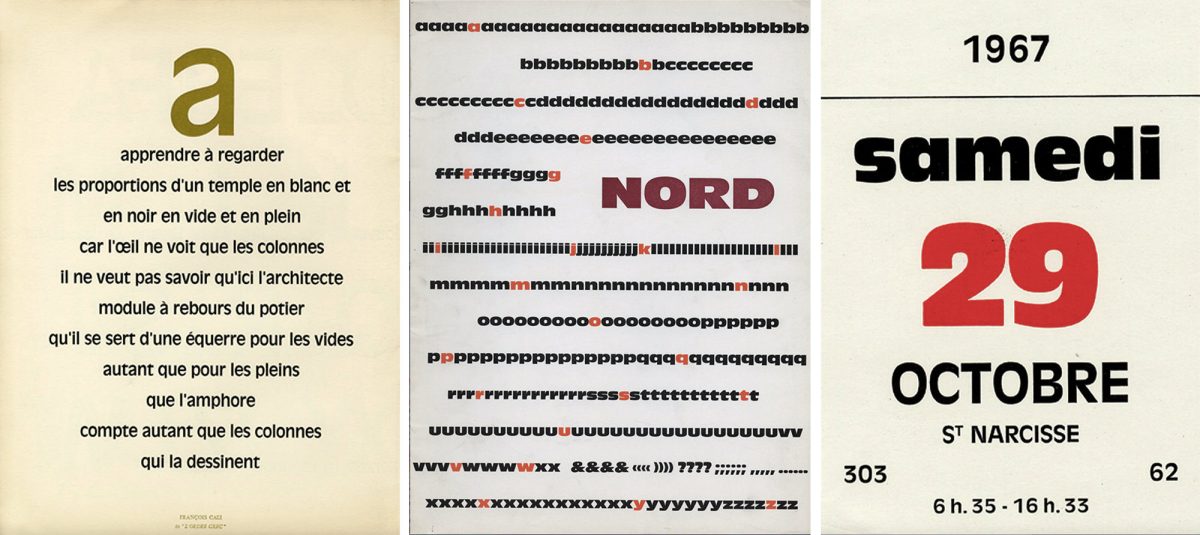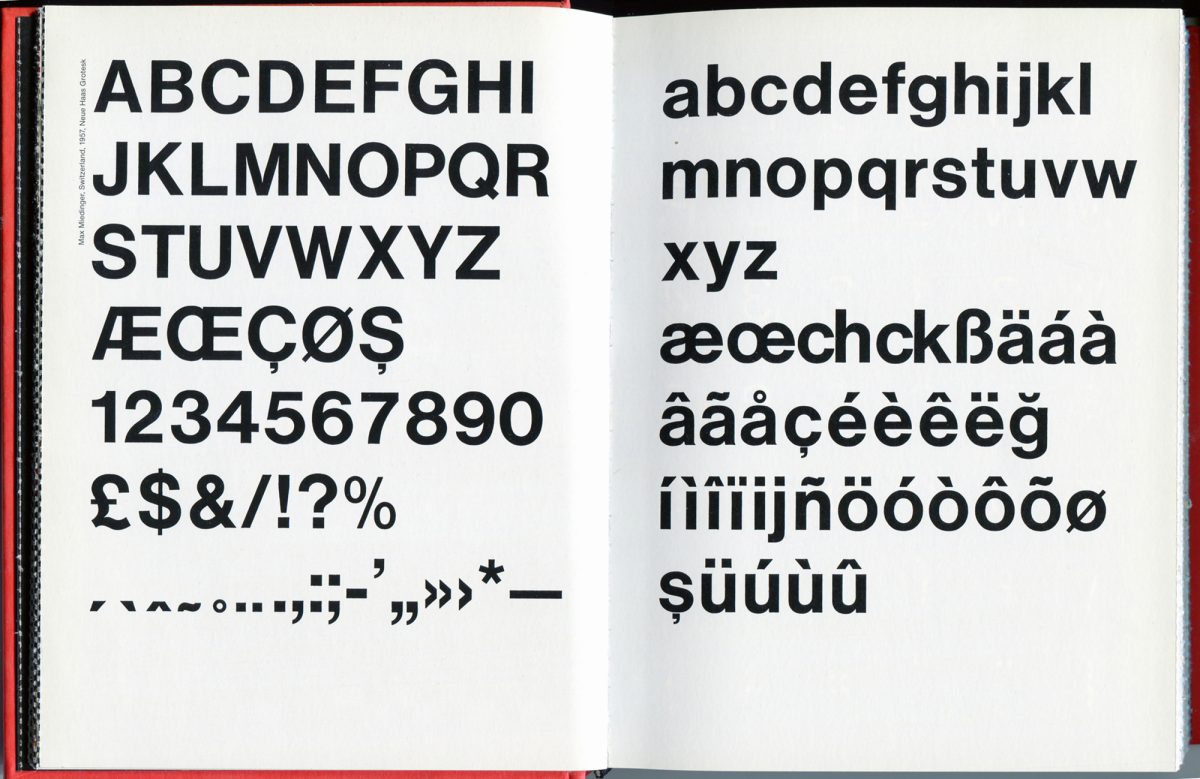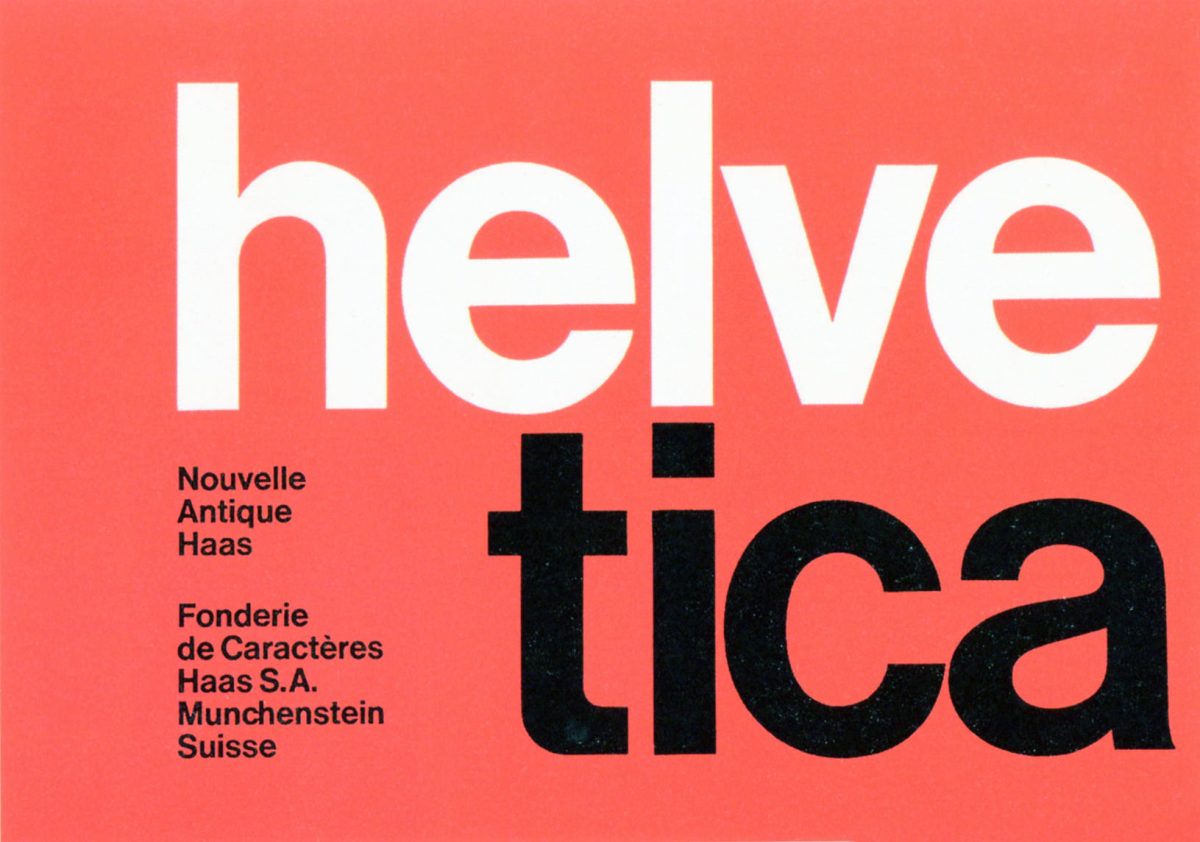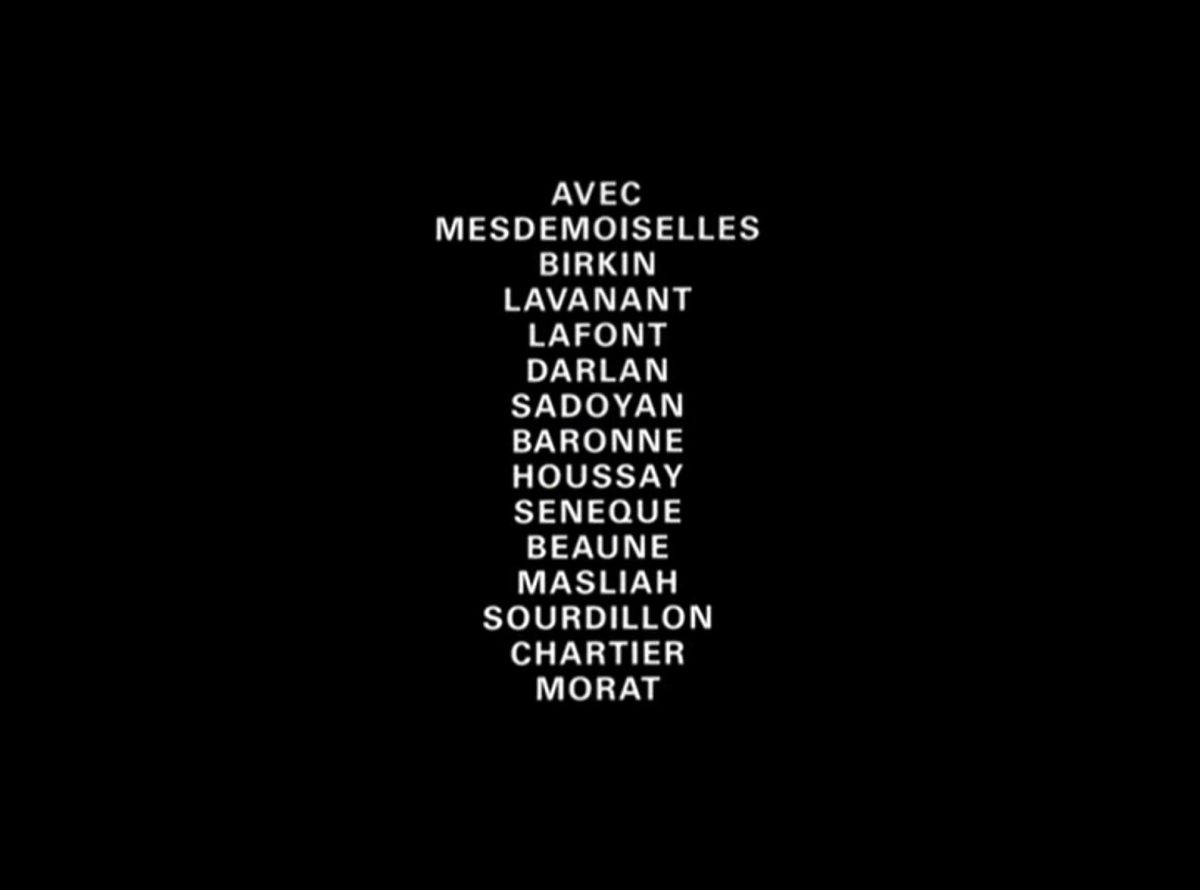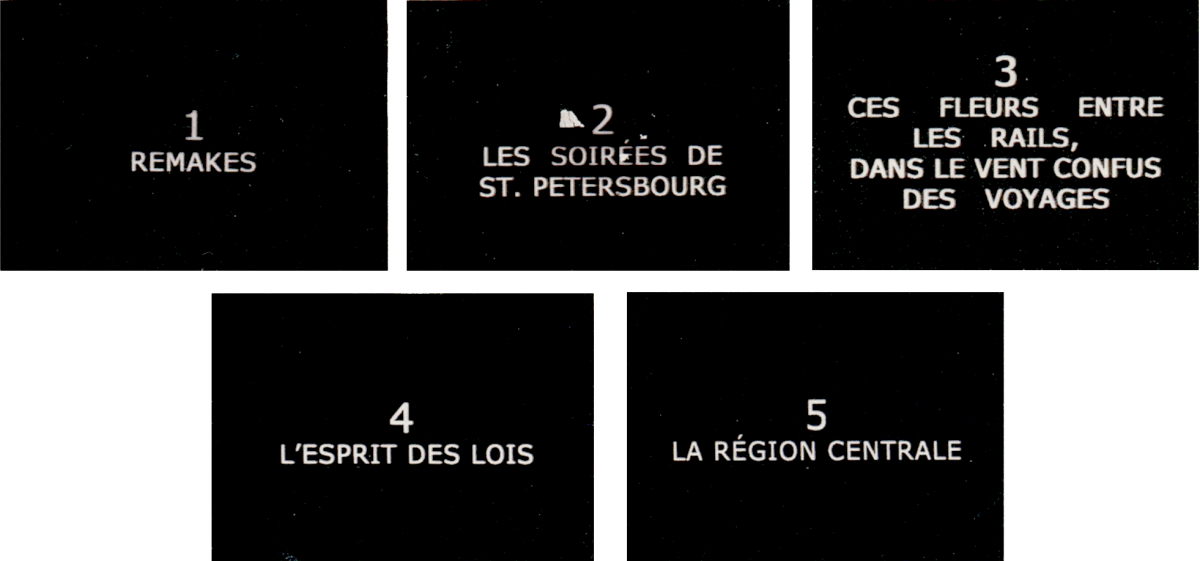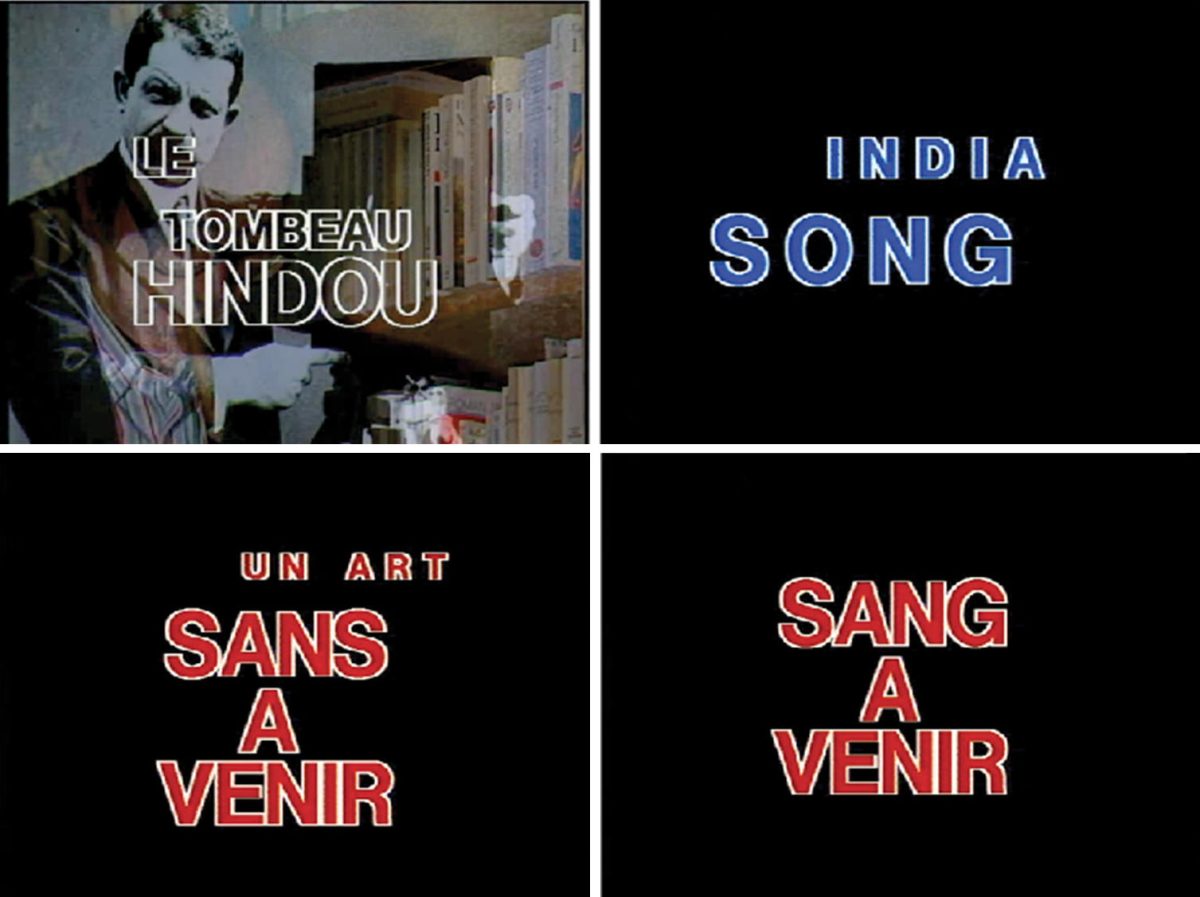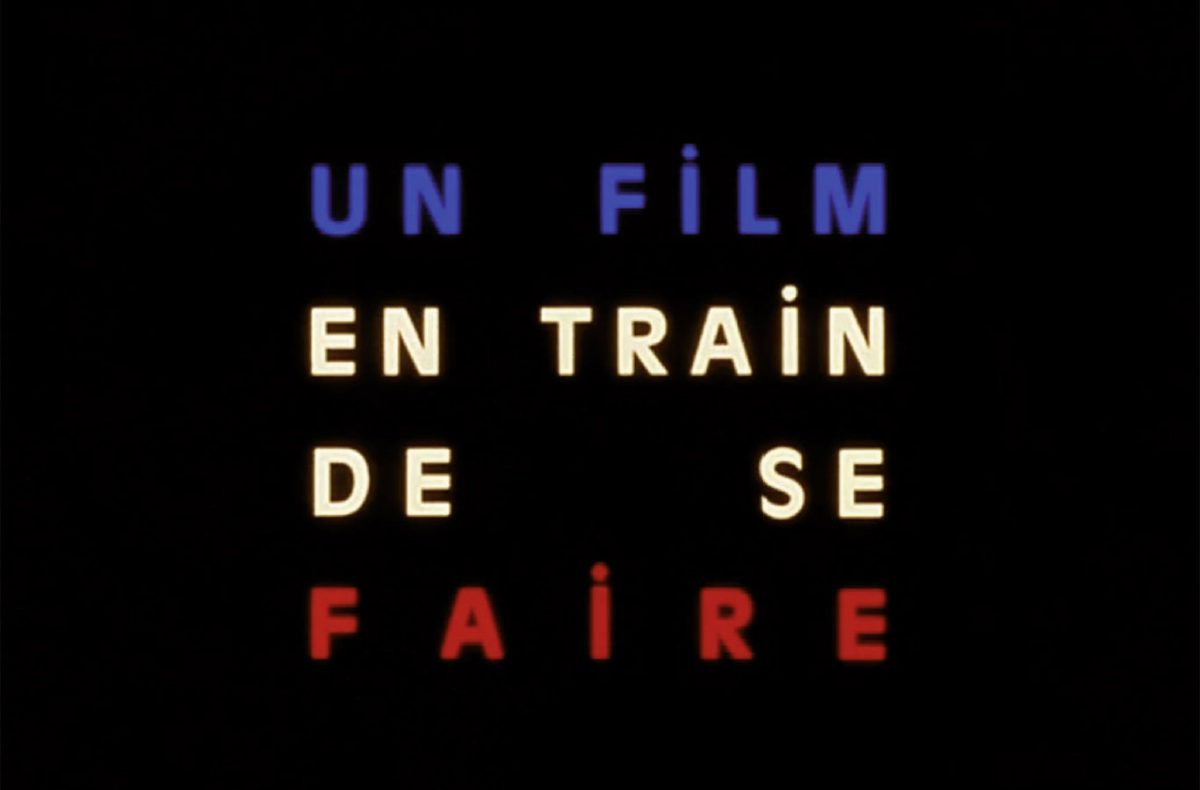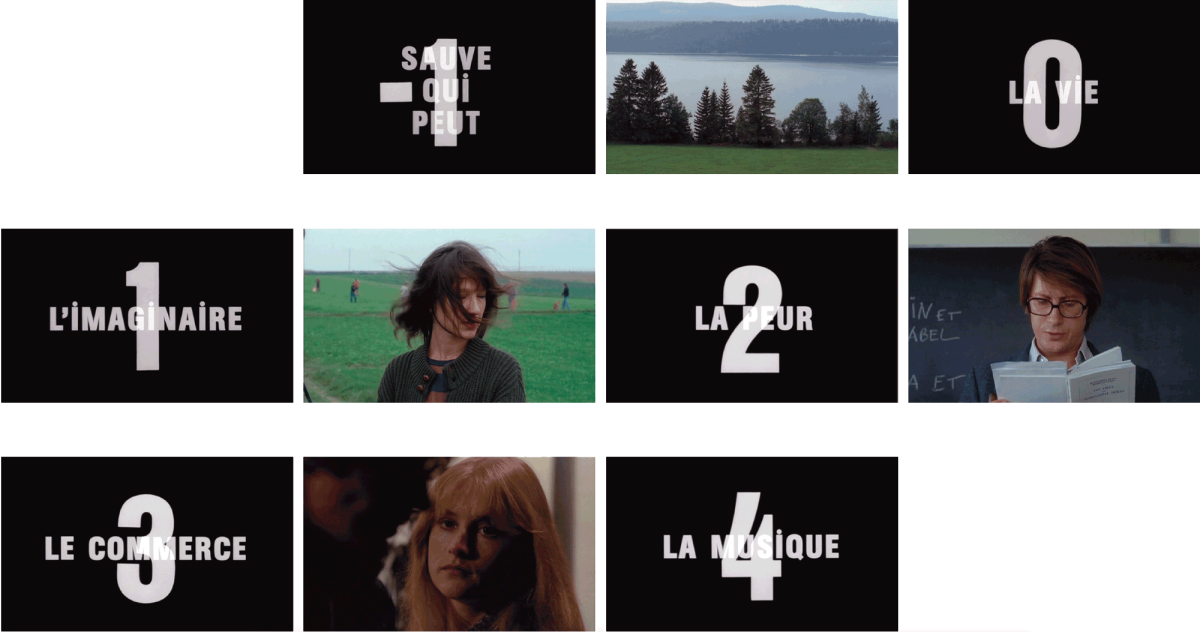
Jean-Luc Godard,
le typographe à la caméra
Imprimée ou filmée, la production graphique de Jean-Luc Godard surprend par sa fréquence et son audace formelle. Qu’il s’agisse d’inserts ou de génériques, de bandes-annonces ou de spots publicitaires, de dossiers de presse ou de numéros spéciaux, l’ensemble de ces réalisations porte sa marque même si sa signature ne l’atteste pas toujours formellement. Une facette particulière de son travail graphique concerne ici l’usage qu’il fait de la typographie.
Héritier de la page imprimée
Si Jean-Luc Godard est le cinéma à lui tout seul, il est aussi un héritier de la page imprimée. La mise en page, et singulièrement la typographie, est pour lui le moyen privilégié d’éprouver chaque fois les rapports paradoxaux du texte et de l’image. Une facette particulière de son travail graphique concerne l’usage qu’il fait de la typographie. Trois temps se dégagent à travers sa filmographie, marqués par le recours à un caractère unique, dont le choix subtil signale des enjeux esthétiques et politiques significatifs.
Pour les deux premiers, il s’agit du très français Antique Olive conçu par Roger Excoffon entre 1965 et 1967 auquel succède le symbole de la typographie suisse, l’Helvetica, des années 1980 à 2010. Le troisième temps se distingue par l’usage de polices dites d’écran (Tahoma ou Verdana) dessinées par Matthew Carter. Godard y a recours dans ses deux dernières œuvres à ce jour, Adieu au langage (2014) et Le Livre d’image (2018). Si la typographie a pour fonction première de donner à voir le texte, la question sous-jacente de Godard quels que soient les supports envisagés (vidéo, papier ou pellicule) est une préoccupation de peintre : comment représenter la pensée et quelle couleur (politique et picturale) lui donner. Comment imprimer une pensée en mouvement et s’affranchir de la fixation du texte sur la page ? Comment faire un livre en faisant du cinéma ? La typographie est la médiation visuelle privilégiée par laquelle Godard tente d’en finir avec la concurrence entre le texte et l’image dans la production de la pensée.
De gauche à droite, cartons bleu-blanc-rouge des films « Deux ou trois choses que je sais d’elle » (1966) ;  « La Chinoise » (1967) et « Week-end » (1967), composé en Antique Olive.
Premier temps. Période Antique Olive ou l’ère de la typographie bleu-blanc-rouge
Dans un entretien avec Alain Jouffroy en 1966, Godard résume de façon explicite son usage du bleu-blanc-rouge et la portée qu’il entend lui donner : « Je crois un peu au nationalisme, mais à un nationalisme de poésie, pas du tout politique : j’aime bien que Delacroix soit français et Beethoven allemand… » Et « Vous croyez à “l’âme d’un peuple” ? » l’interroge Jouffroy. « Je ne peux pas l’exprimer ainsi parce que ça a l’air un peu gros, mais c’est un peu ça   ». 1
Graphie latine et héritage de droite
Au carrefour de ramifications complexes, sa référence récurrente à la France s’étend notamment à la typographie. Ainsi au milieu des années soixante, les compositions graphiques de Godard se démarquent par un recours systématique à l’Antique Olive, caractère on ne peut plus français. Son créateur, Roger Excoffon, à travers l’impact de ses différents dessins dans le paysage français, notamment les enseignes de petits commerces (le Mistral, le Banco, le Choc ou encore le Calypso) a façonné une identité visuelle propre au pays dans les années cinquante.
De gauche à droite, extrait du premier spécimen [1960], couverture du spécimen Antique Olive [vers 1959] et ephemera composé en Antique Olive. © Musée de l’imprimerie de Lyon.
De gauche à droite, couvertures des spécimens Mistral [1953], Banco [1951], Choc [1955] et annonce presse, 4e de couverture, « Caractère » n°12, 1958. © Musée de l’imprimerie de Lyon et Archives Excoffon, Rosaz 2017.
Dessin original, caractère Calypso, vers 1957. © Archives Excoffon, Rosaz 2017.
Antoine de Baecque souligne un trait spécifique de la production de Godard au mitan des années soixante, caractérisée par « la volonté constante, voire jusqu’au-boutiste et touchante, d’être contemporain  » 2. La typographie participe de cette inscription dans le temps énoncée par Excoffon dans ses notes préparatoires pour présenter son caractère : « Oublier tout ce qui a été fait et considérer ce que peut être pour nous l’alphabet en 1956. Je cherche en quelque sorte l’archétype, la représentation exacte de l’alphabet inconscient de chacun. Synthèse de tous les facteurs d’influences, avons-nous dit, l’alphabet idéal. » 3
À sa sortie entre 1958 et 1960, l’Antique Olive est d’une nouveauté radicale que le dessinateur de caractères hollandais, Gerard Unger, commente rétrospectivement en ces termes : « Une réponse d’Excoffon au style dominé par le pragmatisme et l’objectivité suisse. » 4 Signe de l’attention aiguisée du cinéaste à la typographie, cette linéale communément utilisée dans la publicité est identifiée par Godard pour son originalité, et déplacée dans un usage inattendu dans de nombreux bancs-titrages qui ponctuent ses films, parmi eux Pierrot le fou (1965) ; La Chinoise (1967) et Week-end (1967), qui se distinguent également, par l’emploi des couleurs du drapeau. Dans son alliance chromatique et typographique, cet ensemble constitue un condensé désigné ici par les termes de « goût français », expression calquée sur « goût hollandois », en référence à la classification établie dans le Manuel typographique (1764-1766) de Pierre-Simon Fournier.
Générique du film « Pierrot le fou », 1965. Vidéo et captures d’écran.
Dans cette expression qui associe la forme et le style d’un caractère à une langue, le mot « goût » renvoie également à l’idée d’une saveur. Pour son difficile exercice de définition d’un standard français en typographie, Unger adoptera précisément ce biais, imagé et évocateur, dans « La Frontière de la bière et du vin ». 5 Analysant l’influence de la typographie française sur sa propre pratique — et tout particulièrement celle des caractères d’Excoffon —, le typographe hollandais s’affranchit de questions d’ordre identitaire pour ouvrir sur la métaphore culinaire, ou l’analogie : « une sorte d’équivalent typographique des gestes que l’on fait pour accompagner une discussion, de l’ail et son odeur et des autres herbes que l’on met dans la cuisine…  ». 6